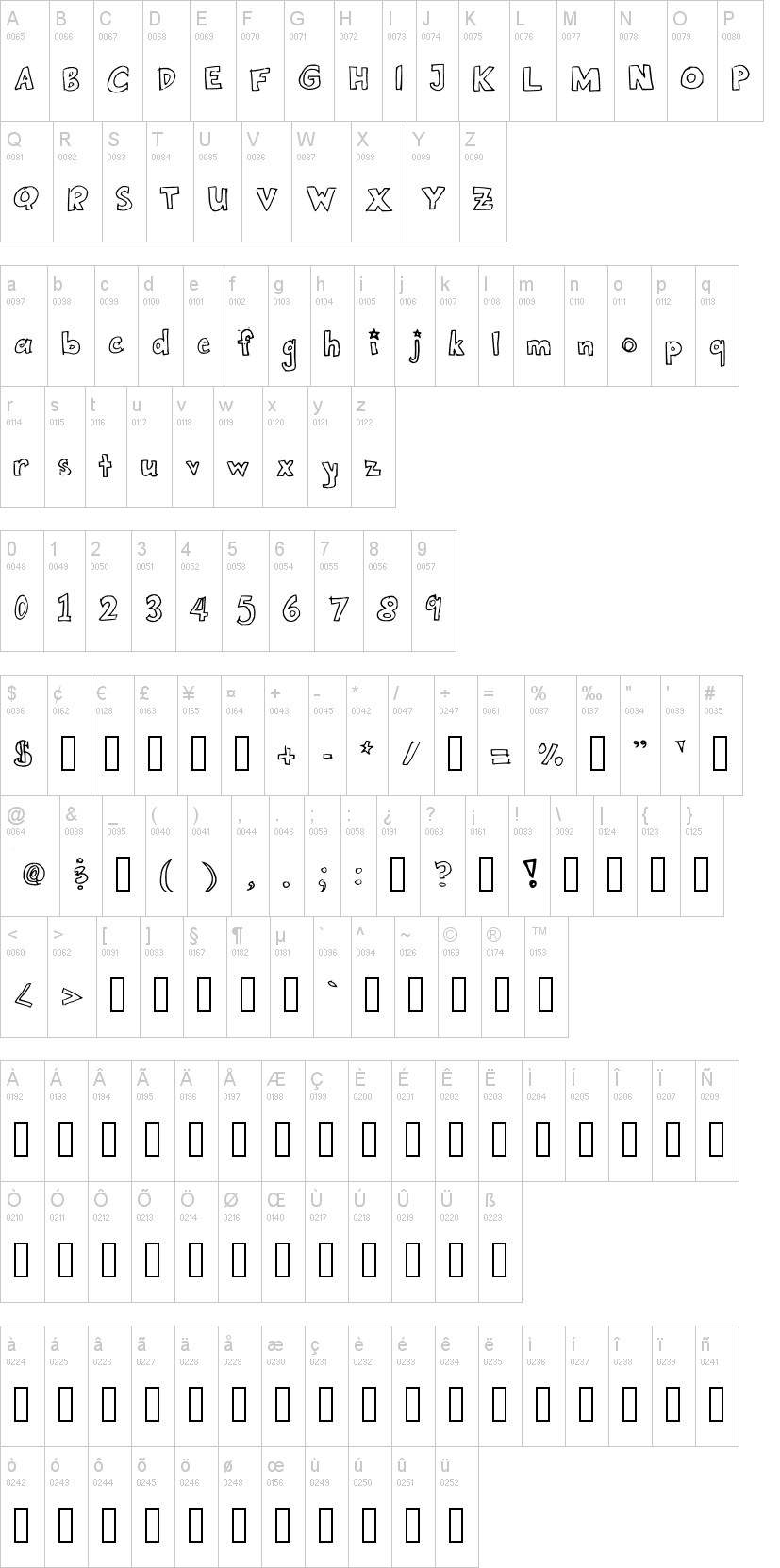
Bubbles Make Me Happy
? Bubbles Make Me Happy 是一款由Fontfabric创作的手写字体,它具有简单、温柔、可爱的外观。这款字体有着清晰的曲线和温柔的笔触,适合用于把握幸福和快乐的场合,比如标题、海报、卡片、T恤等等。它还可以用于创作简笔画、插画、拼贴画等,给你的作品增添一抹活力和欢乐的气息。
Bubbles Make Me Happy是一款非常不错的手写艺术字体,具有很好的视觉感,适合于文化类的宣传设计、商业类品牌的广告和产品包装设计以及个性化文字排版等较多场景。
Bubbles Make Me Happy字符映射图